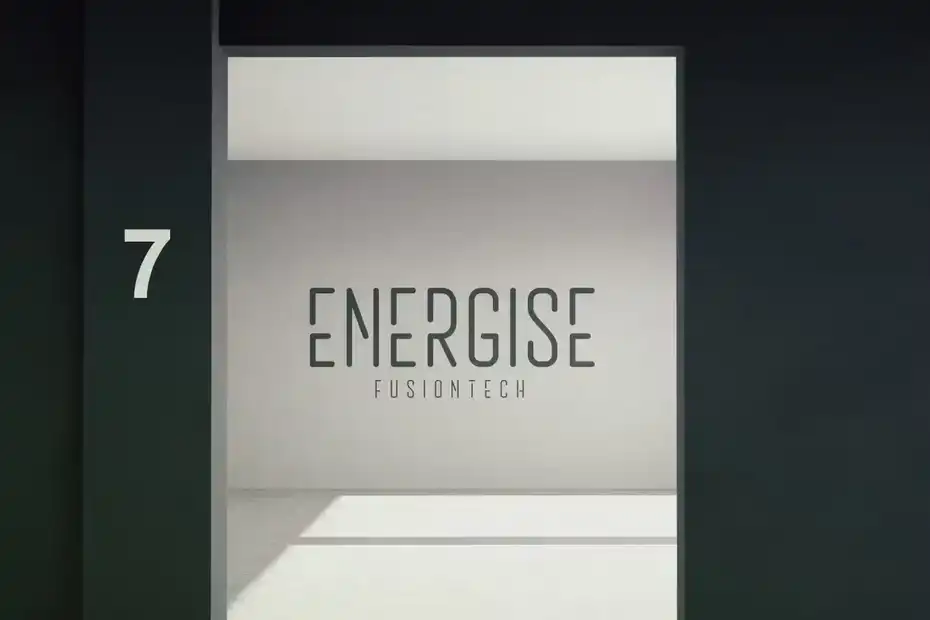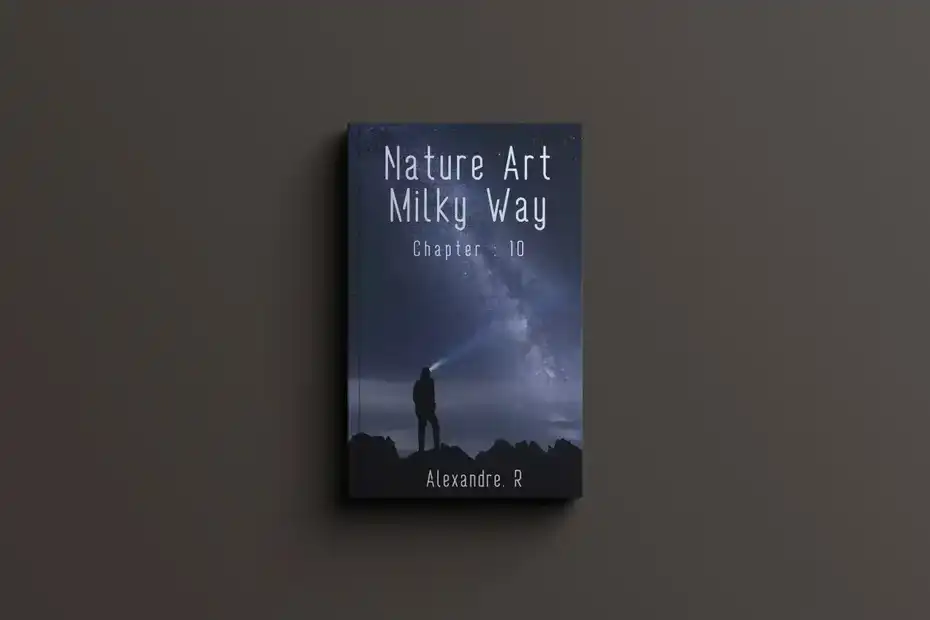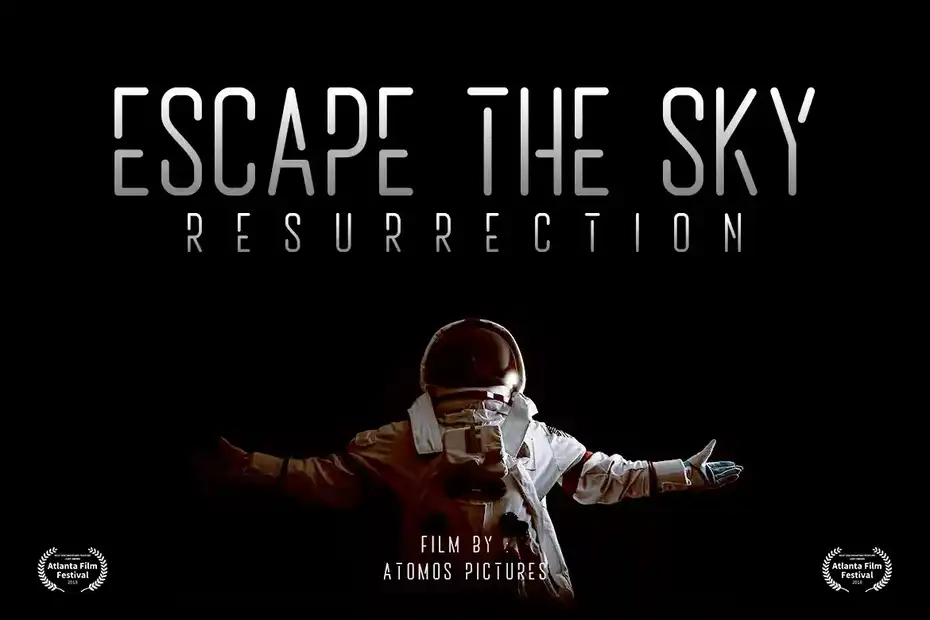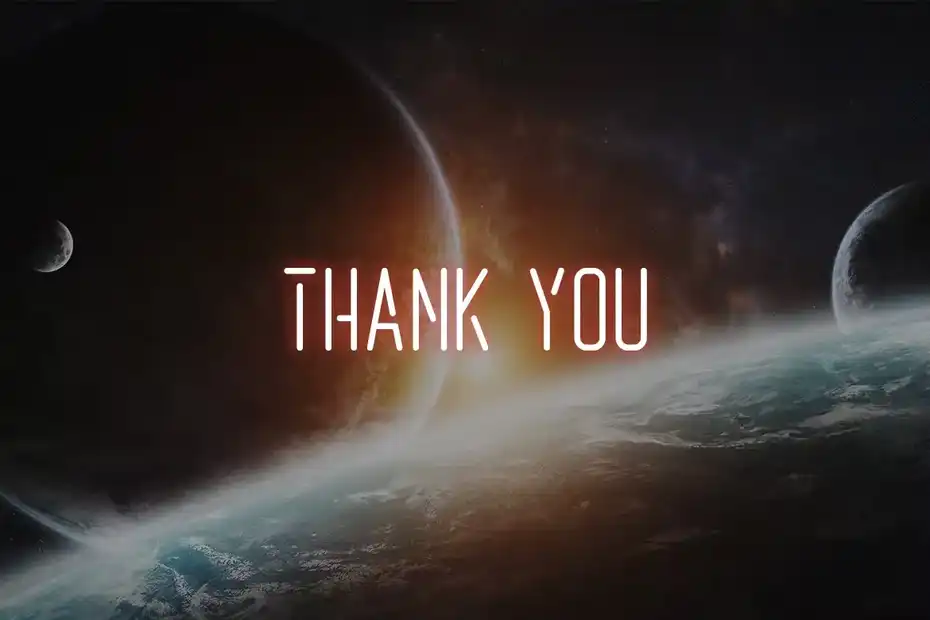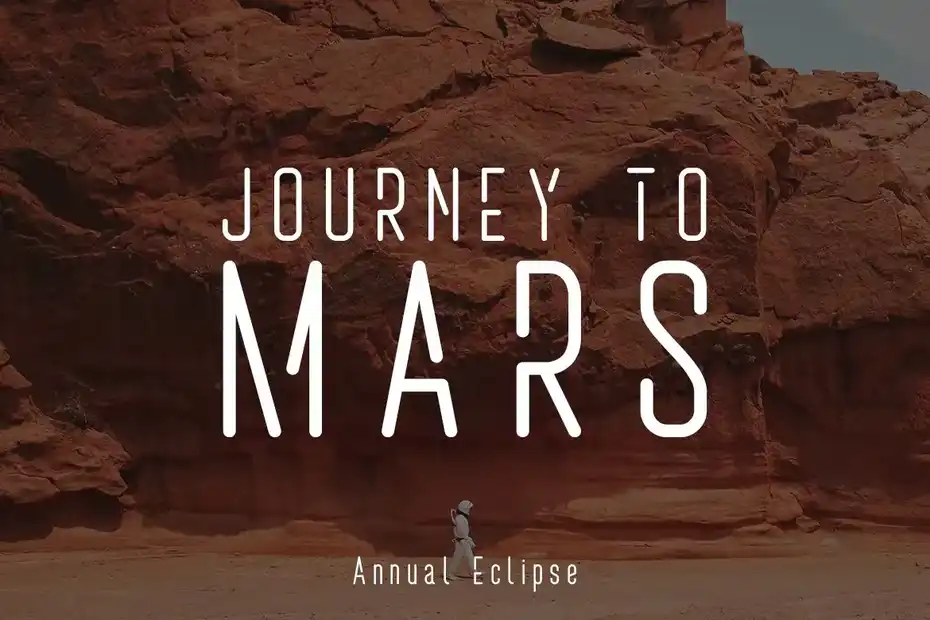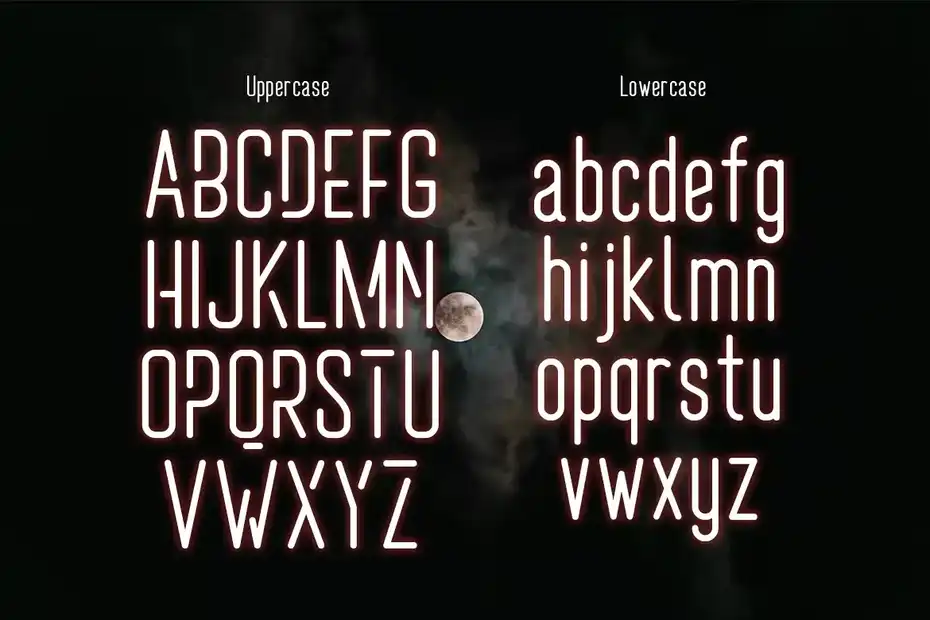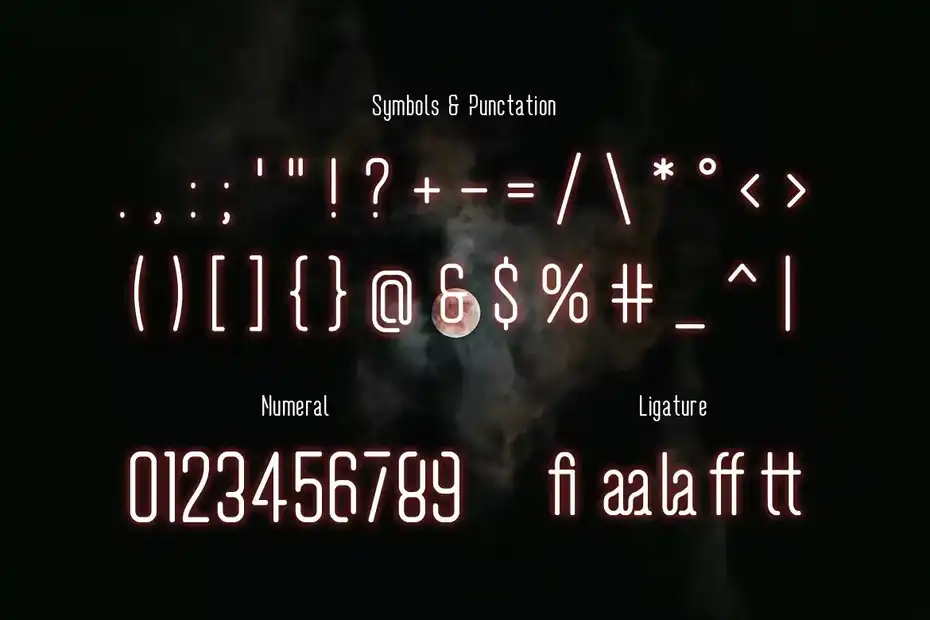
دانلود فونت فضانورد Wavemax – Space Futuristic Font
دانلود فونت فضانورد Wavemax – Space Futuristic Font : این مجموعه شامل یک فونت فانتزی است که برای فیلم، مستند، لوگو، پوستر، بازی، جلد کتاب، تایتل و غیره مناسب میباشد. از بخش دانلود فونت انگلیسی در سیجی کوک می توانید آرشیو کامل فونت های حرفه ای و با کیفیت را مشاهده کنید.